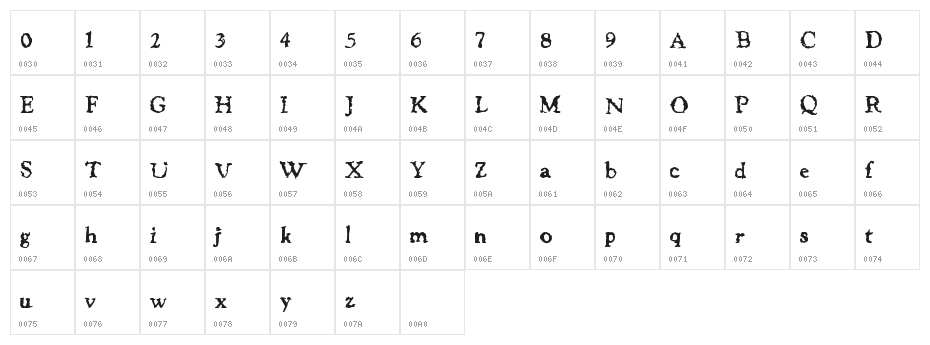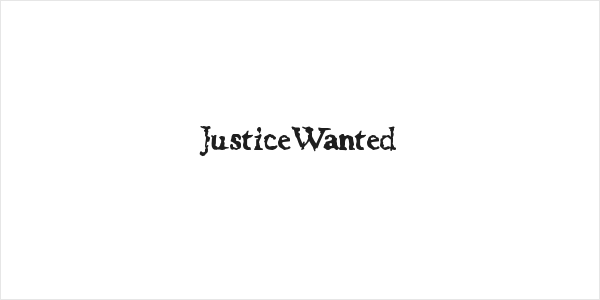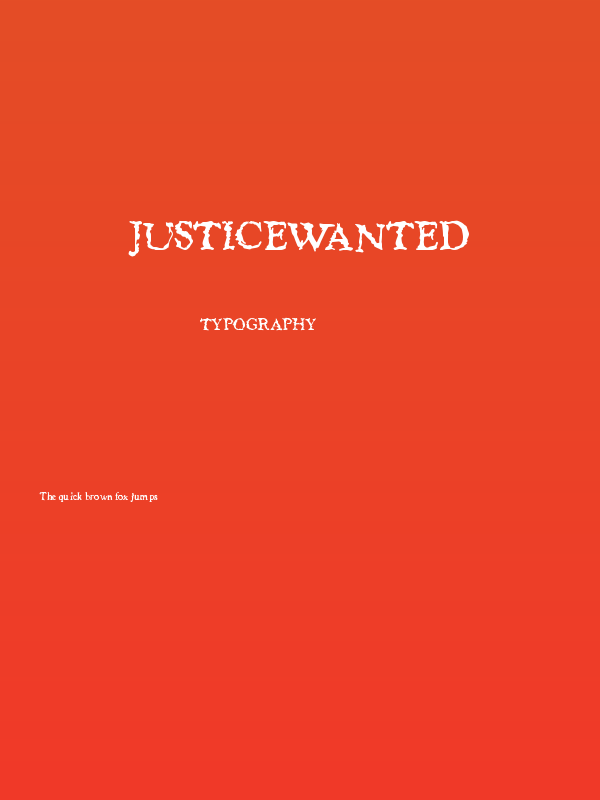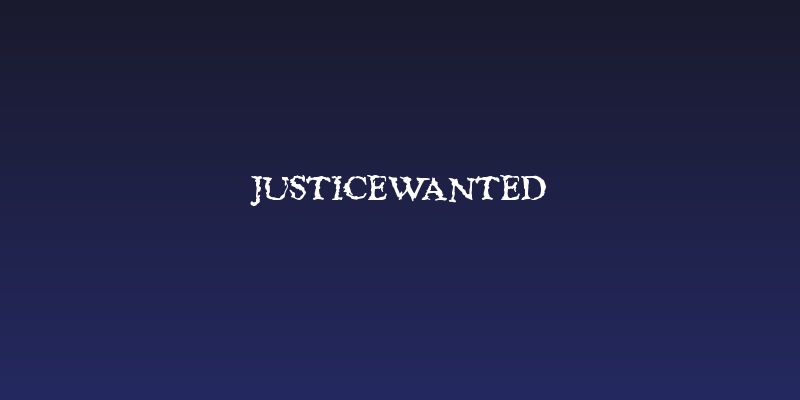
JusticeWanted Font
✎ Distorted Eroded
| Proiecte propuse | Ideal for themed posters, event flyers, branding for rustic or vintage products, and creative design projects that require a bold, attention-grabbing typeface. |